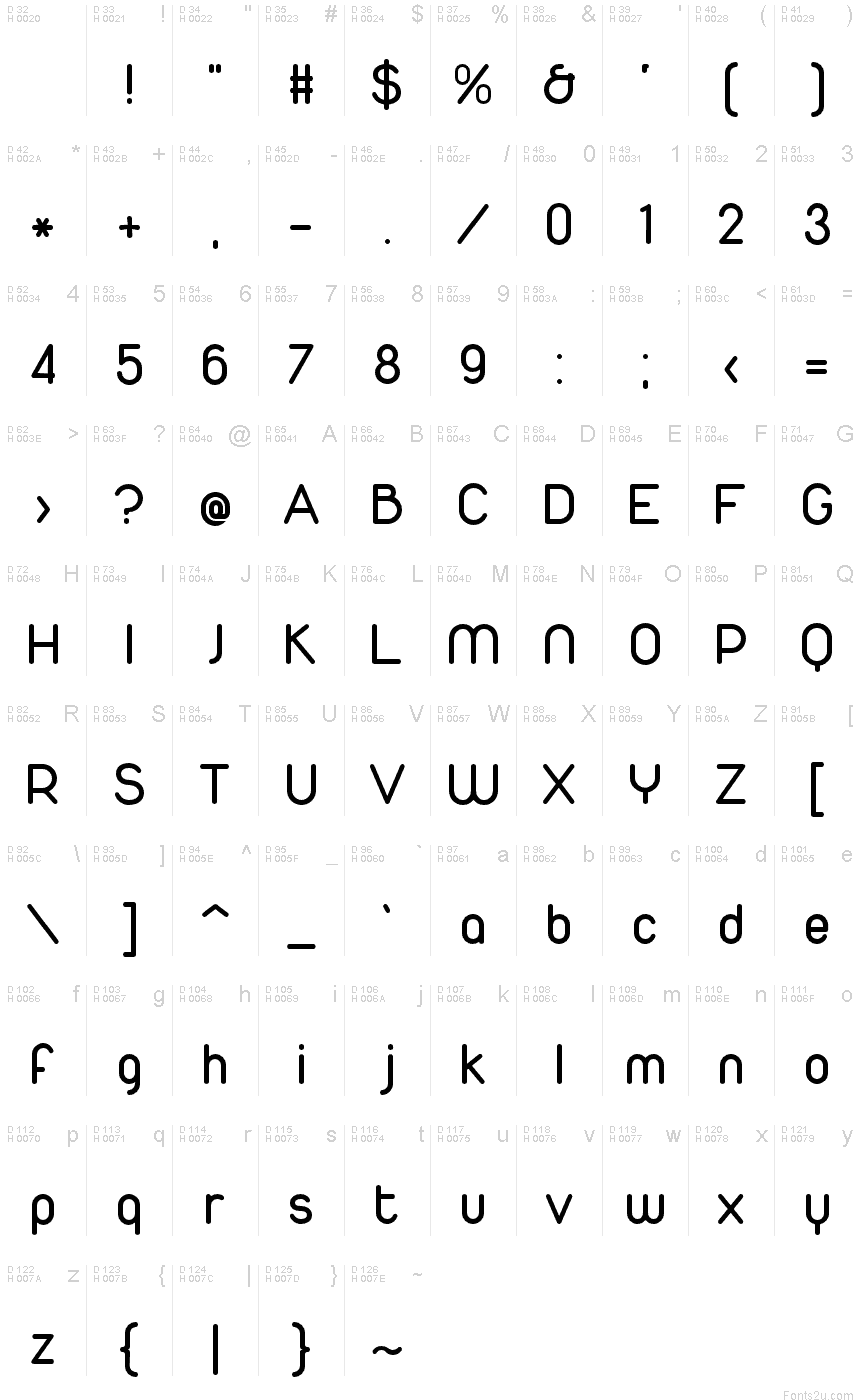
Duepuntozero هو خط مجاني بتصميم دائري بلا زوائد من استوديو Kmzero، يضفي إيقاعاً ناعماً وانسيابياً على الخطوط المعاصرة. توازن منحنياته الواسعة، وخطوطه ذات السماكة الموحدة تقريباً، وأعمدته النظيفة بين النظام الهندسي والطابع الودود والمرح قليلاً.
يخلق هيكله المفتوح والمنساب إيقاعاً بصرياً هادئاً في هويات العلامات التجارية وواجهات التطبيقات، بينما تمنح أشكاله الدائرية السخية للعناوين التحريرية ورسومات الفعاليات صوتاً حديثاً وودوداً. اختر هذا الخط المجاني لتغليف المنتجات أو أنظمة التوجيه، حيث يمكن للهندسة البسيطة أن تتماشى بشكل مريح مع الأيقونات والصور والتصاميم المتباعدة.